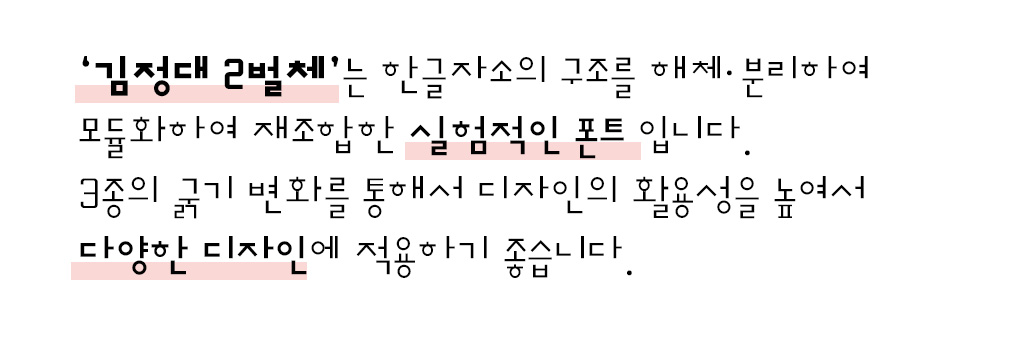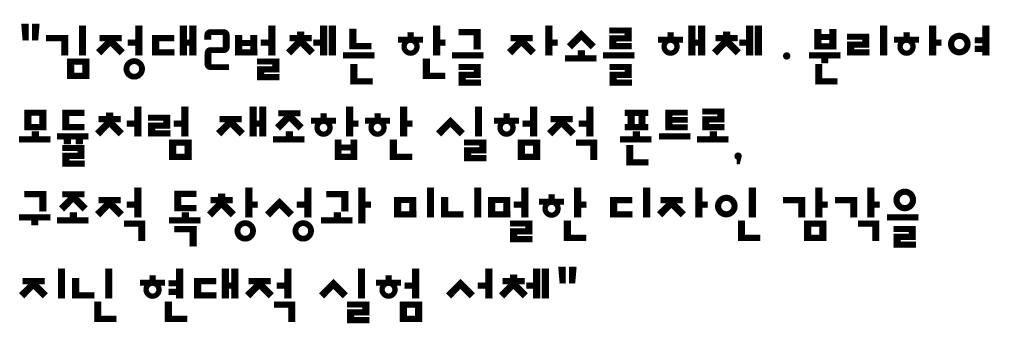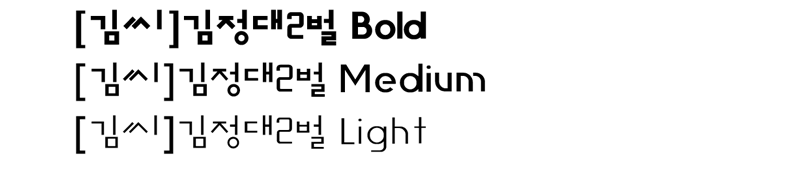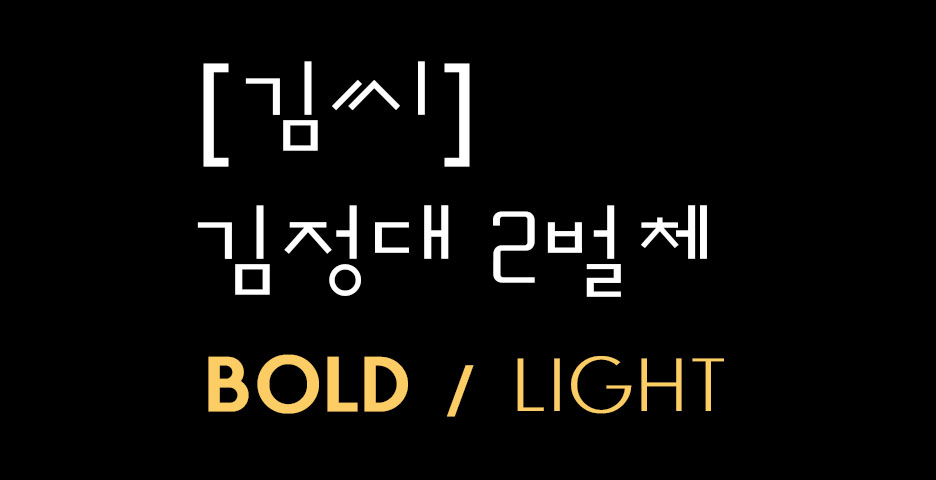
● 구조적 실험성
한글의 자음과 모음을 결합된 상태가 아니라, 각 자소를 “벌” 단위로 독립시켜 글자를 새롭게 조합.
전통적인 정자 구조에서 벗어나, 해체와 재구성을 통한 실험적 접근.
● 모듈화된 디자인
●● 김정대 2벌체 개발 컨셉
자소 하나하나를 규칙적으로 나누어 배치하여, 모듈러 폰트처럼 작동.
글자가 퍼즐처럼 맞춰지는 느낌을 강조.
● 현대적 미니멀리즘
획을 단순화하고 불필요한 장식을 배제.
군더더기 없는 직선 위주의 형태로 미래지향적이고 실험적인 인상.
● 타이포그래피적 메시지
“한글은 결합의 언어”라는 기존 인식을 깨고, 자모 단위의 분절된 시각성을 통해 새로운 리듬과 공간감을 제시.
독특한 낮섦을 통해 관객에게 “한글 구조에 대한 재인식”을 유도.
● [김씨]김정대 2벌체 3종(LIGHT / MEDIUM / BOLD
●● 폰트구성